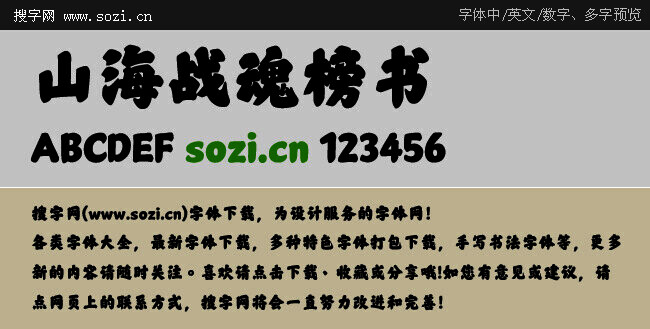
山海戰(zhàn)魂榜書
搜字網(wǎng)提供一款山海戰(zhàn)魂榜書中文書法字體下載,該字體雄健有力,霸氣外露,在粗細的縱橫間,擁有非常規(guī)的張力特性。該字體的筆畫充滿力量感,組合搭配極富強烈的節(jié)奏感,融入楷書特點,使字體的視覺效果有力、寬厚、方正,充滿了穩(wěn)重感和設計感。適合標題設計、包裝設計、海報設計、廣告設計等應用。